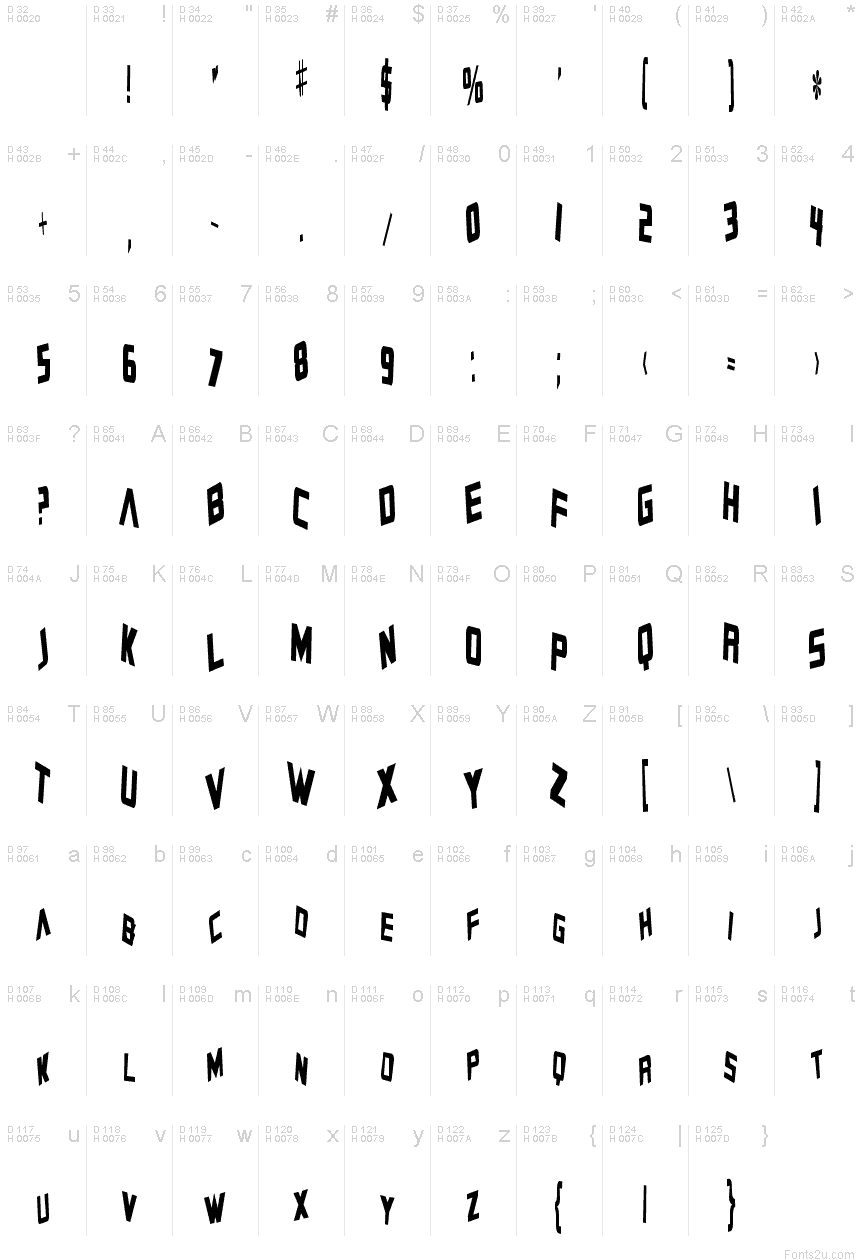
Zero Gravity هو خط عرض (display font) مجاني بطابع الخيال العلمي، أطلقته ShyWedge عام 1999. يقوم الخط بثني الحروف الكبيرة في إيقاع حاد وغير متوازن يبدو وكأنه مستوحى من ملصقات الفضاء القديمة. تميل الحروف وتلتوي وتستدق في اتجاهات مختلفة، مع زوايا حادة وهندسة غير منتظمة تمنح الخط بالكامل طابعاً عائماً مضاداً للجاذبية، بعيداً عن المظهر المستقبلي المصقول.
يناسب هذا الخط بشكل طبيعي منشورات الخيال العلمي القديمة (ريترو)، وشعارات الألعاب، وأغلفة المجلات، وعناوين الأفلام، والعناوين القصيرة للملصقات حيث يمكن لخط مجاني يتمتع بهذا القدر من الحيوية أن يؤدي المهمة بسرعة. استخدمه عندما تريد أن تبدو الحروف غير مستقرة وكأنها محلقة في الهواء، وهو مثالي للعناوين المكونة من كلمة واحدة، أو جمل الأغلفة، أو الأحرف الاستهلالية التي تستفيد من صورته الظلية المشوهة.